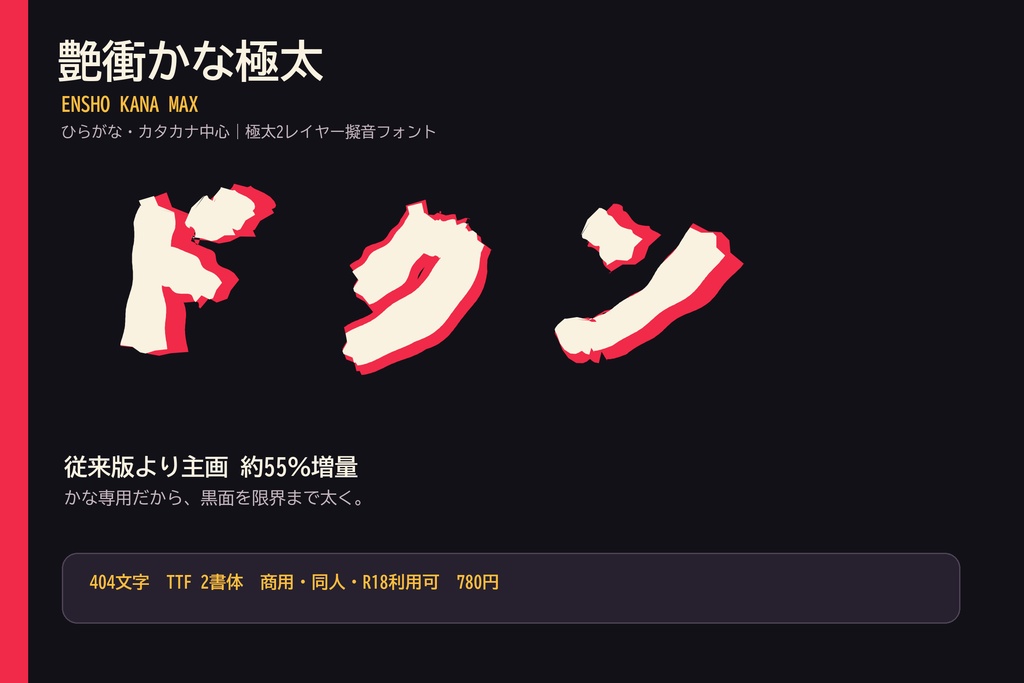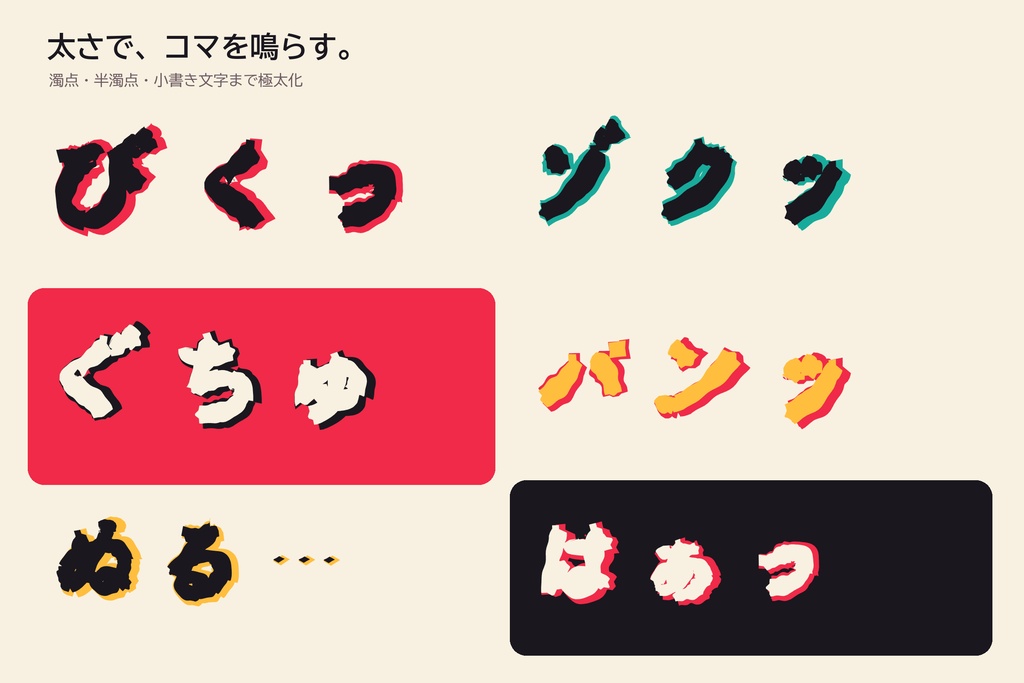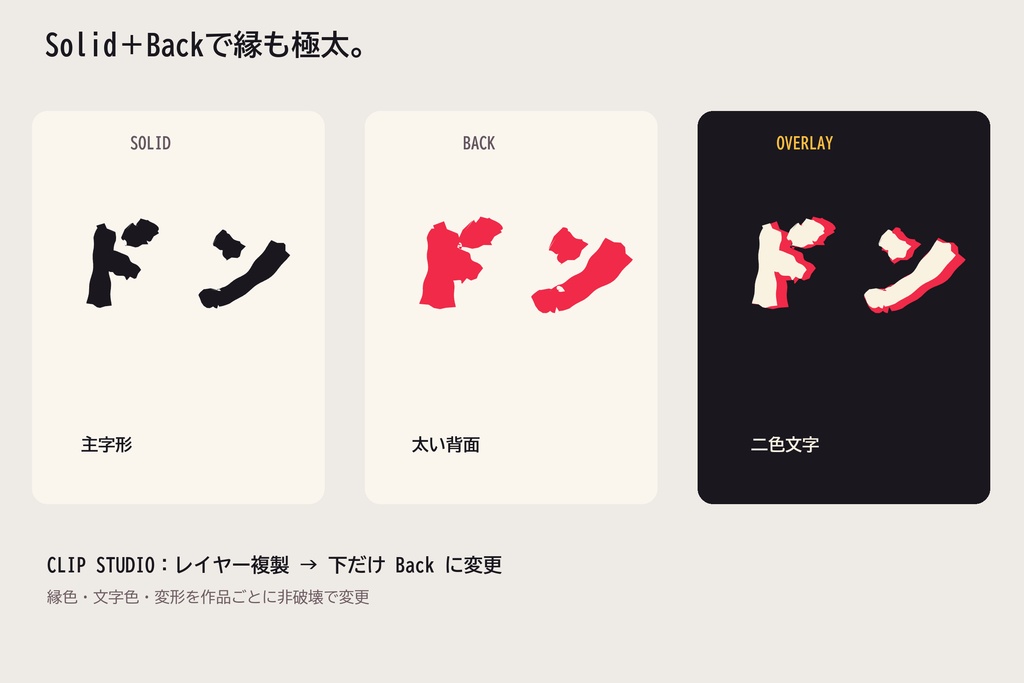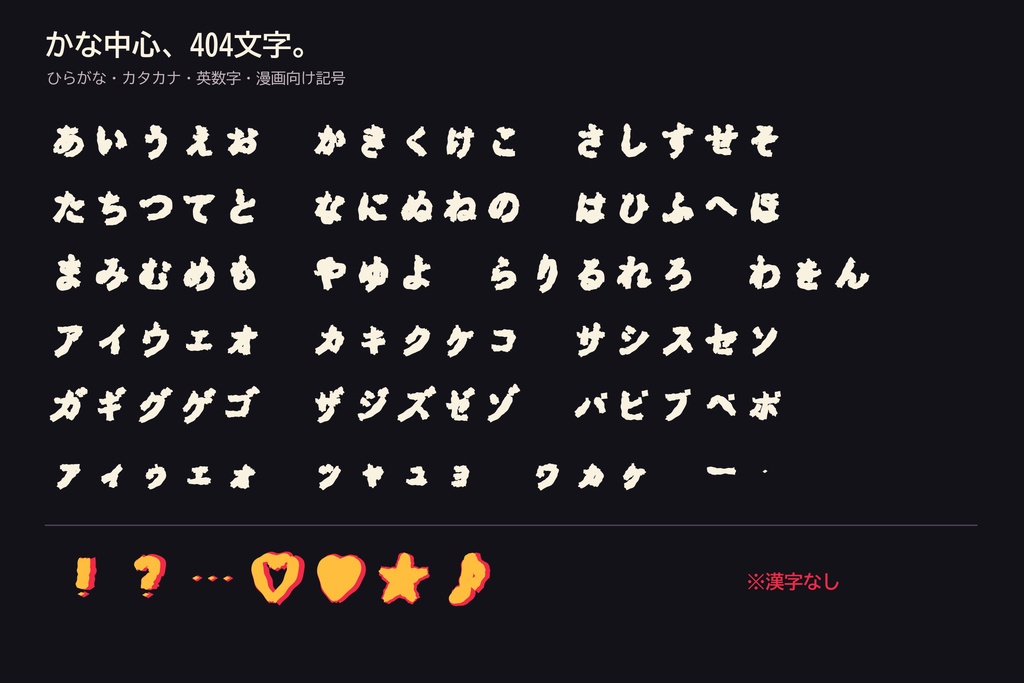
【極太・商用R18可】艶衝かな極太|2レイヤー擬音フォント
【艶衝かな極太 / ENSHO KANA MAX】 もっと太く。もっと黒く。 「ドクン」「びくっ」「ぐちゅ」「パンッ」を、大きな黒面で置ける ひらがな・カタカナ中心の極太2レイヤー擬音フォントです。 ■ 価格 780円 ■ 2レイヤー ・Solid:極太の主字形 ・Back:縁・影用の太い背面 同じ文字、サイズ、位置で重ねるだけで二色文字や縁を作れます。 CLIP STUDIO PAINTでは、テキストレイヤーを複製して下だけBackへ変更します。 ■ 収録 404文字 ・ひらがな、カタカナ ・濁音、半濁音、小書き文字 ・半角/全角英数字 ・基本約物、漫画向け記号 ・ハート、星、音符 ※漢字は収録していません。 ■ 形式 TrueType(TTF)2書体 / Windows・macOS ■ 利用 個人・商用利用可。クレジット不要。 同人、商業、成人向け(R18)作品、漫画、電子書籍、動画、配信、 ロゴ、装丁、広告、受託制作に使用できます。 画像化後の変形、着色、縁取りも可能です。 フォントファイルの再配布、共有、転売、改変フォントの配布は禁止です。 詳細はZIP内の利用規約をご確認ください。